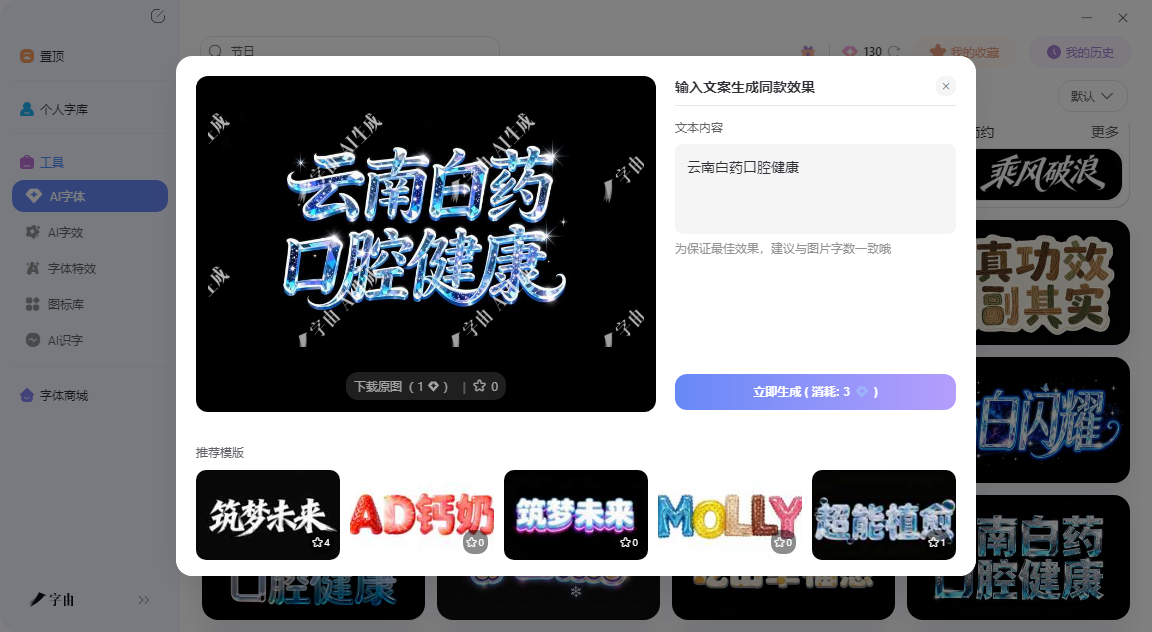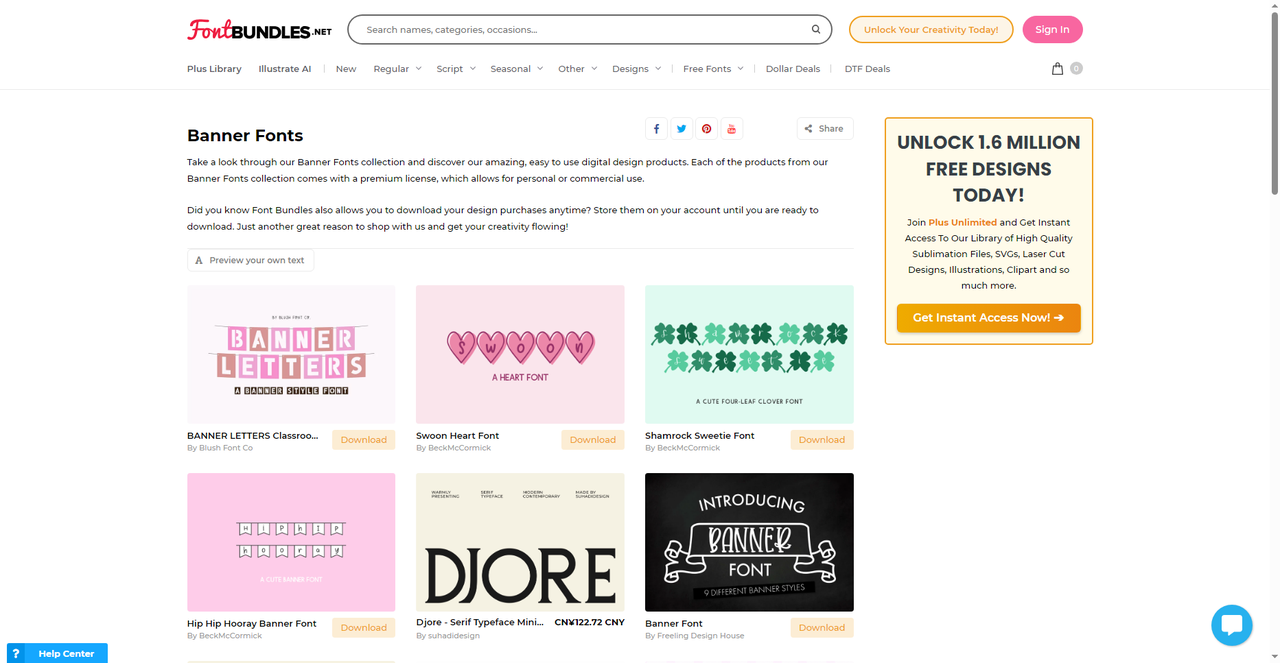
广告牌字体怎么选?这5个工具一键生成大标题效果
你有没有注意过路边那些广告牌?有的你开车路过,远远就能看清上面写的什么;有的你走近了还得眯着眼辨认。区别在哪?不是内容,是字体。广告牌字体有特殊的要求:字要够粗,笔画不能太细;结构要稳,不能花里胡哨影响识别;远距离看还要有冲击力。这不是随便选个字体就能搞定的。今天实测了5款广告牌字体相关工具,从在线生成到专业字库,覆盖了不同场景的需求。
先聊字由。很多人知道字由是字体管理工具,但它的AI字体功能,其实是做广告牌标题的捷径。
为什么广告牌字体需要“特效”?一块好的广告牌,不是把字打上去就行。餐饮店的招牌可能需要霓虹灯效果,商场的促销海报可能需要金属质感,国潮品牌的广告可能需要水墨书法风。这些效果用普通字体做不出来,用PS做又太慢。字由的AI字体模板库,专门解决了这个问题。打开字由客户端,进入“AI工具”下的“AI字体”,左侧筛选栏里有“国潮风”“霓虹灯”“金属质感”“手写书法”“电商促销”“科技感”等大类。每个大类下面都有几十款适合做大标题的特效模板。
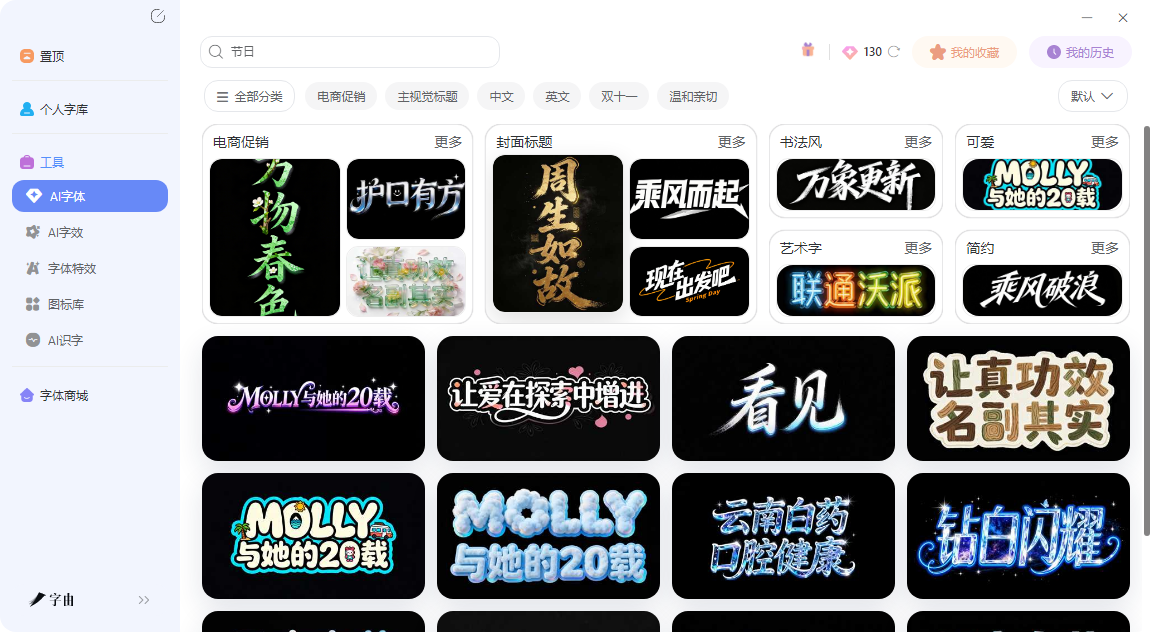
实际操作:从模板到出图只需要简单的几个步骤。你不需要懂任何设计。假设你要做一个奶茶店的夏季促销海报,标题是“杨枝甘露 限时尝鲜”。打开字由AI字体,在“风格”里选“国潮风”或“电商促销”,翻到一款顺眼的模板,点“做同款”,在右侧输入框把模板里的文字换成你的文案,点“立即生成”。10到15秒后,一张高清艺术字图片就出来了。下载透明背景的PNG,直接放进海报里。整个过程,从打开客户端到拿到图,用不了一分钟。
2、Banner Fonts
第二个工具是Banner Fonts(来自Font Bundles平台)。这是一个专门做横幅风格字体的集合。注意:这里的“Banner”不是指网页Banner,而是指物理横幅——比如节日挂的“Happy Birthday”横幅、婚礼上的装饰字母串。这些字体的特点是:每个字母都是独立的装饰元素。比如“BANNER LETTERS Classroom”字体,每个字母像是一块小旗帜或者卡片;“A HEART FONT”是心形装饰字体;“Swoon Heart Font”是带有心形连笔的花体;“Shamrock Sweetie Font”是三叶草装饰字体。
这类字体不适合做商业广告牌,但非常适合做派对横幅、节日装饰、手账标题、社交媒体配图。如果你要办生日派对,想打印一条“Happy Birthday”的字母串,用这类字体每个字母独立排版,剪下来串成横幅,效果比普通字体好得多。Font Bundles平台上的产品都带有高级许可证,允许个人和商业使用,下载后可以放心用于装饰品制作。
3、Adobe Fonts
第三个工具是Adobe Fonts中的Miller Banner字体。这是专业字体设计公司Carter & Cone Type Inc.的作品,属于Miller字体家族的一个子系列。“Banner”在这里不是指横幅,而是指这类字体专门为大尺寸展示(如广告牌、海报、大标题)而设计。Miller Banner的特点是:笔画对比度经过优化,在放大的情况下依然保持优雅的比例;衬线设计清晰,远距离阅读不费力;字重有多种选择(Light、Light Italic等),适应不同背景。
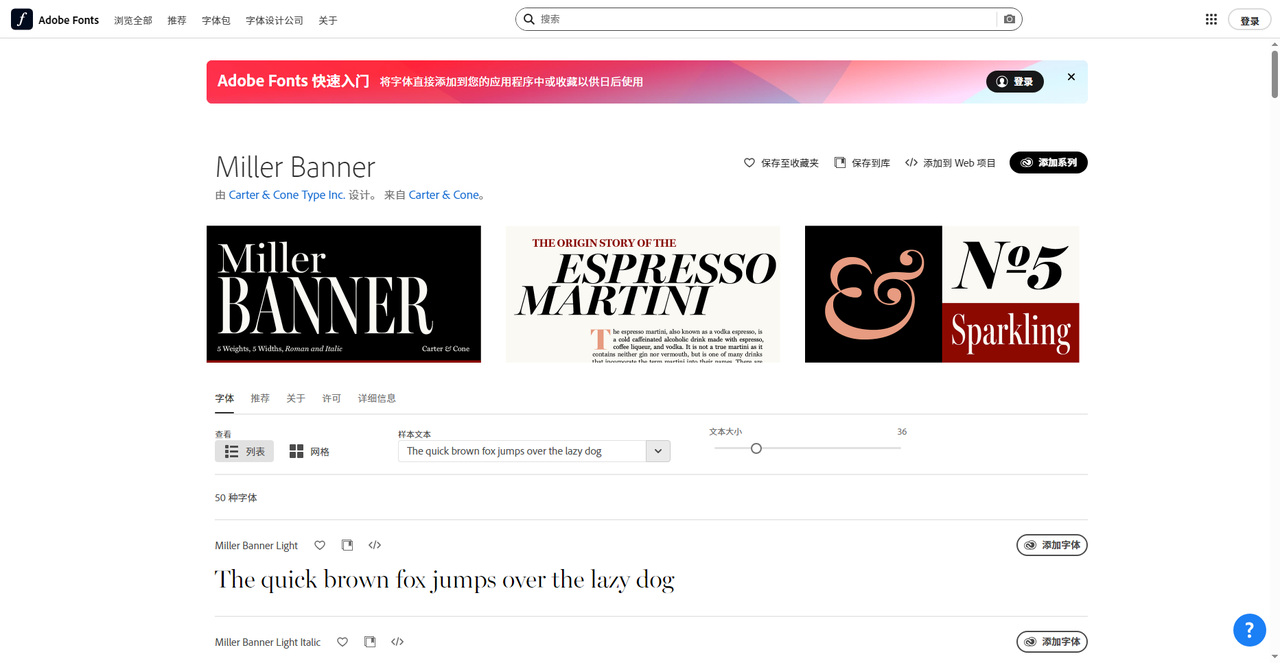
4、FontStylesBanner
第四个工具是FontStylesBanner。这是一个免费的字体聚合网站,专门收集“Banner fonts”——也就是适合做横幅、大标题的粗体字。网站分类里有“Banner fonts”标签,点击后可以看到大量适合广告牌的字体。截图里展示了“Katana”字体,由Iconian Fonts设计,属于Foreign look / Chinese & Japan分类,是一款带有东方风格的粗体字,适合做亚洲主题的广告牌。用户可以输入自定义文字预览效果,调节字号(比如56pt),然后免费下载。
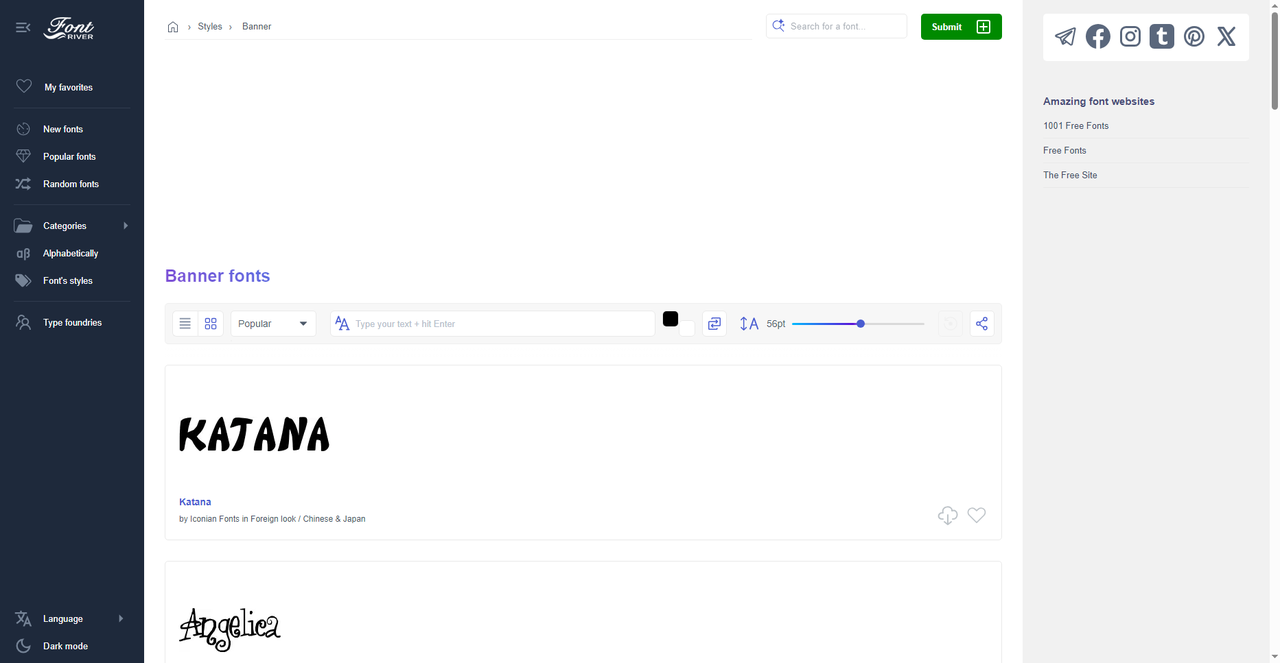
5、Resource Boy
第五个工具是Resource Boy。这是一个设计资源聚合平台,提供字体、纹理、特效、样机等资源。它的“Banner Fonts”分类下,展示了多款适合做横幅标题的字体,比如“Bread Mate Font”“Banerton Font”“Bottle Coffee Font”“Dinofans Font”“Delta Font”。这些字体的风格比较多样:有的像面包店的手写招牌体,有的像咖啡店的现代粗体,有的像儿童产品的圆润字体。每个字体都有预览图,点击可以下载。Resource Boy上的资源大多是免费或低价(如1美元),适合预算有限的设计师。如果你正在做一个小型店铺的招牌设计,想找一款有个性又不贵的字体,Resource Boy值得翻一翻。
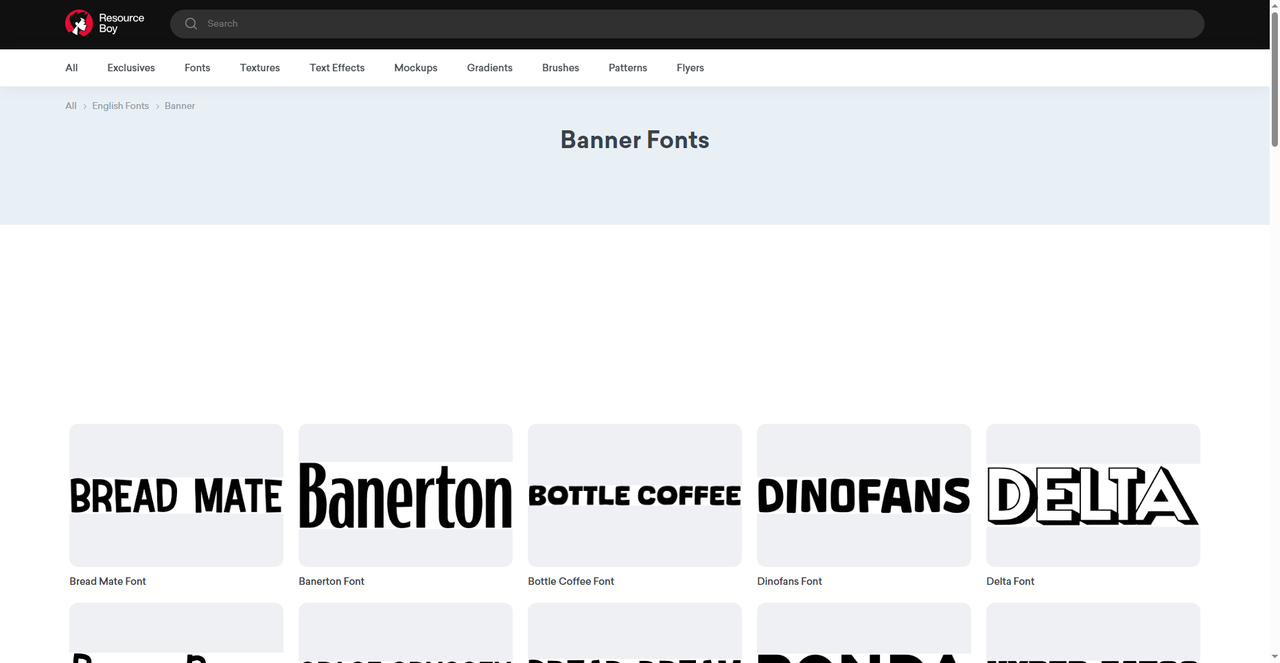
做广告牌字体,关键不是“哪个工具最好”,而是“你的项目需要什么”。字由的AI字体最适合快速出图,400多种特效模板覆盖霓虹、金属、国潮、促销等场景,生成的图片直接能用,版权清晰;如果你是专业设计师,给客户做户外广告,字由的免费商用字体库配合AI特效模板,能帮你快速出方案,定稿后再用专业字体精修。不管哪种,先想清楚广告牌要挂在哪里、多远距离看、什么光线条件,再决定字体的粗细和特效。字够粗、够稳、远距离能看清——这是广告牌字体永远的第一原则。